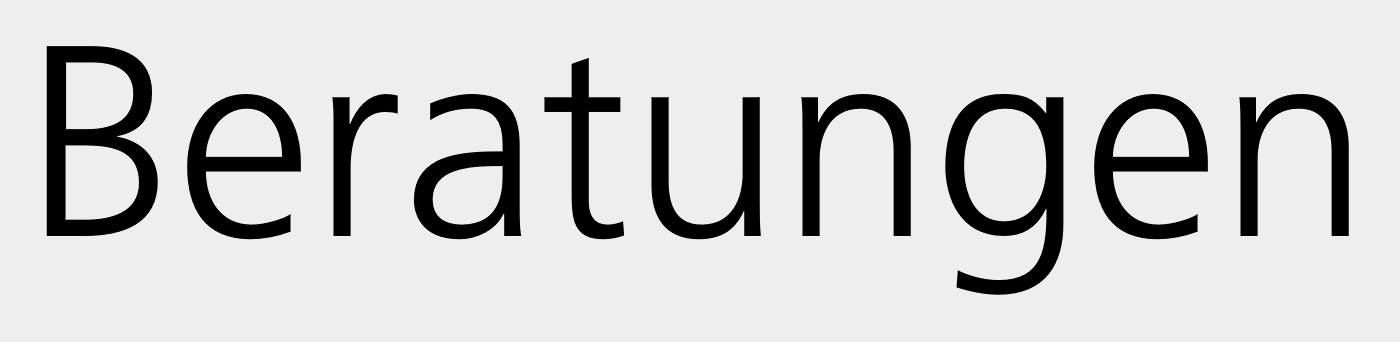
Welche Schriftart ist das?
kann mir jemand weiterhelfen? Suche den Namen folgender Schrift.
bei der Auflösung werden Schriftensuchmaschinen nicht sehr genau arbeiten. Mein erster Tipp wäre ein Frutiger-Clon ... irgend was ähnliches die Frutiger, Frutiger Next oder ggf. Myriad. Bei den Frutigers passt aber das ß nicht. Humanist 777 BT hätte das passende ß.
Ralf hat Recht. Ich habe mich da verguckt und auf das ß der Frutiger Next geschielt. Die Originalfrutiger passt doch.
Vielleicht findet man in der Quelle PDF-Dateien zum Analysieren oder kann die Schrift als Webfont finden?
Das klein a macht mir da aber noch Sorgen ... Na ja ... das ist jetzt erst mal anderer Leute Problem.
Am ß verguckt!